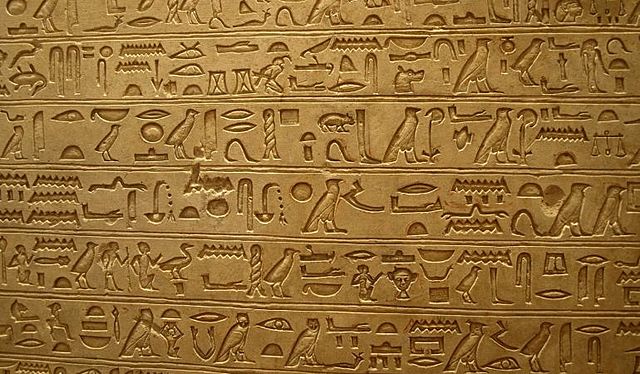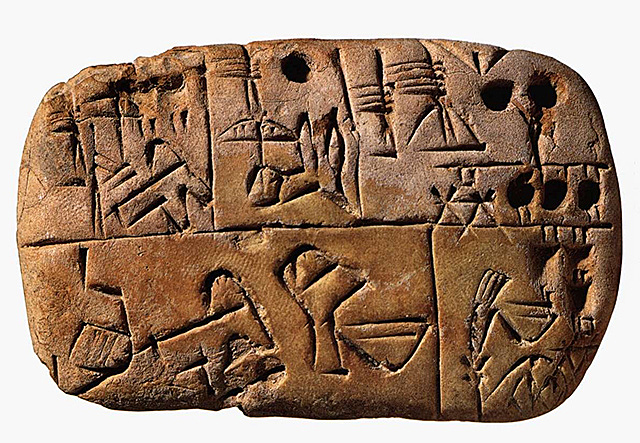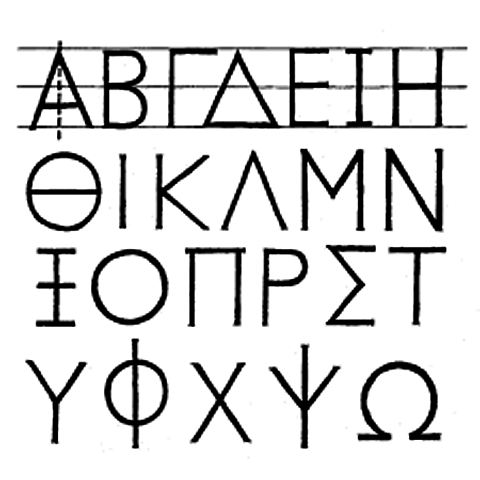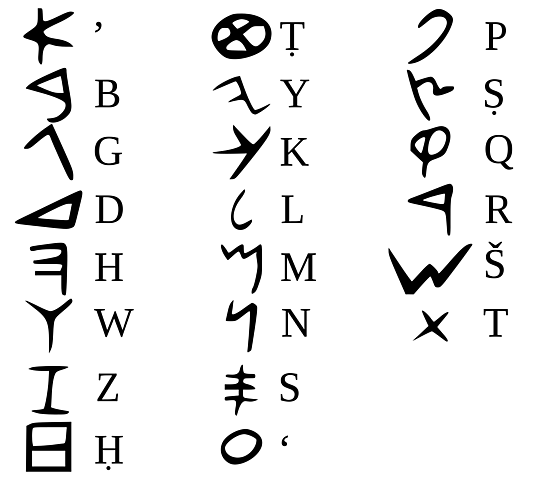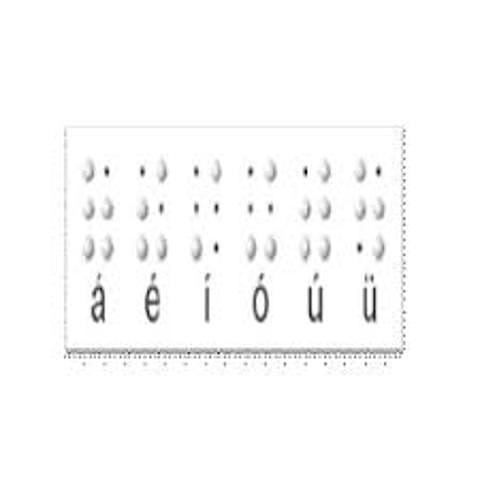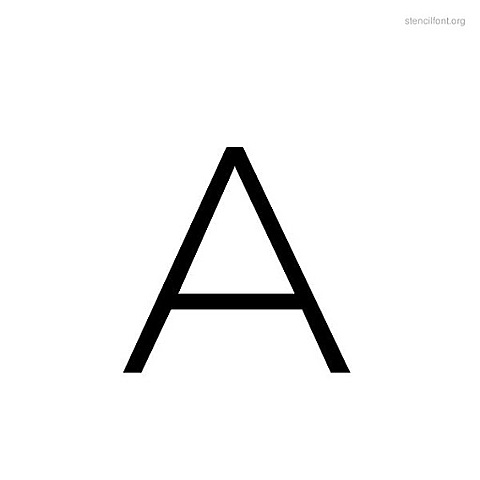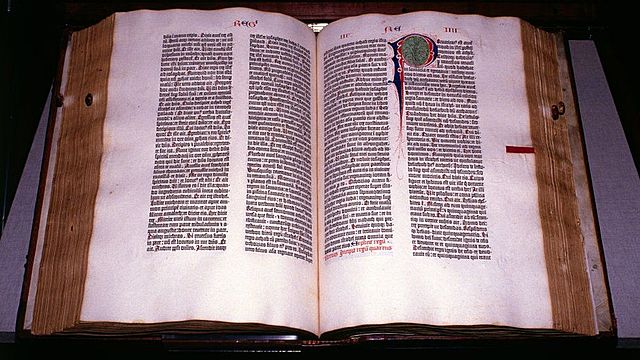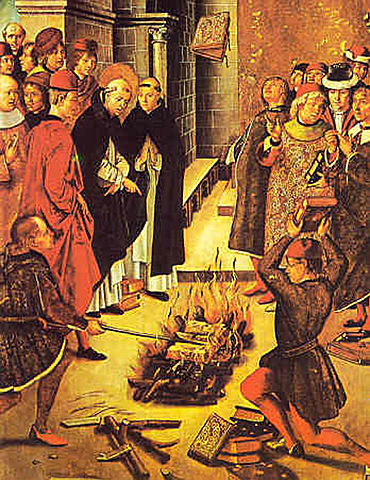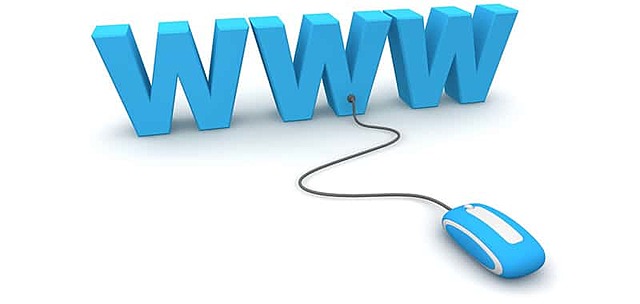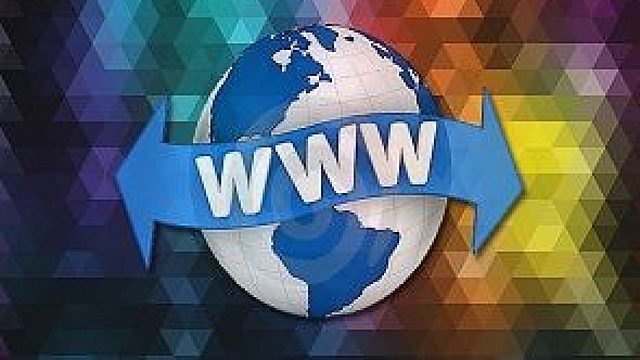
en mesopotamia se empieza escribir en cuneiforme sobre tablilla
aparece la escritura expresada por medio de dibujos en cuevas
los egipcios empiezan a utilizar los jeroglíficos como escritura
Aparece la escritura en arcilla cocida en mesopotamia
estos surgen en el momento que los mesopotamicos empiezan a representar objetos o conceptos
los cananeos crean y hacen uso de un alfabeto de 27 letras
aparecen las primeras escrituras chinas sobre caparazones
estos crean signos o dibujos que tenían fonética
Los fenicios crean el primer alfabeto como guía para el nuevo
estos adoptan el alfabeto de los fenicios e introducen las vocales
Estas letras derivan del alfabeto griego y romano, atención a al estética los romanos no usaban separación entre la letra
Los chinos hacen creación del papel
El papel hace reemplazo del pergamino en europa
en Europa los monjes con el tiempo fueron mejorando su escritura para luego introducir su pro`pio estilo
aparece la nueva escritura semiuncial
por fin se atribuye de manera oficial la invención de la imprenta
se redescubrio la tipografía román y se desarrollo con altas y bajas para mejorar su lectura
Inicia la impresión de la obra mas importante en el mundo "La biblia de Gutenberg"
el papa julio III hace presencia ordenando la quema de libros hebreos
William Austin Burt patenta una maquina llamada tipógrafo
Se crea el World Wide Web
La compañía remington patenta la primera unidad de maquina de escribir
las compañías empiezan a depender fuertemente de las computadoras
La World Wide Web es lanzada al publico
estos se crean con el fin de poder realizar diseños a las paginas Web
Aparición del libro digital y proyectos de difusión literaria como el Gutenberg
Hotmail nos permitía comunicarnos fácilmente y realizando uso de emoticones
Este producto se lanza con el propósito de conectar a estudiantes universitarios
Jam Koum quien era anteriormente el director de equipo de operaciones de Yahoo! crea Whats App
se inaugura la nueva red de microblogging Twitter
Nace google+, gmail como correos personales o laborales